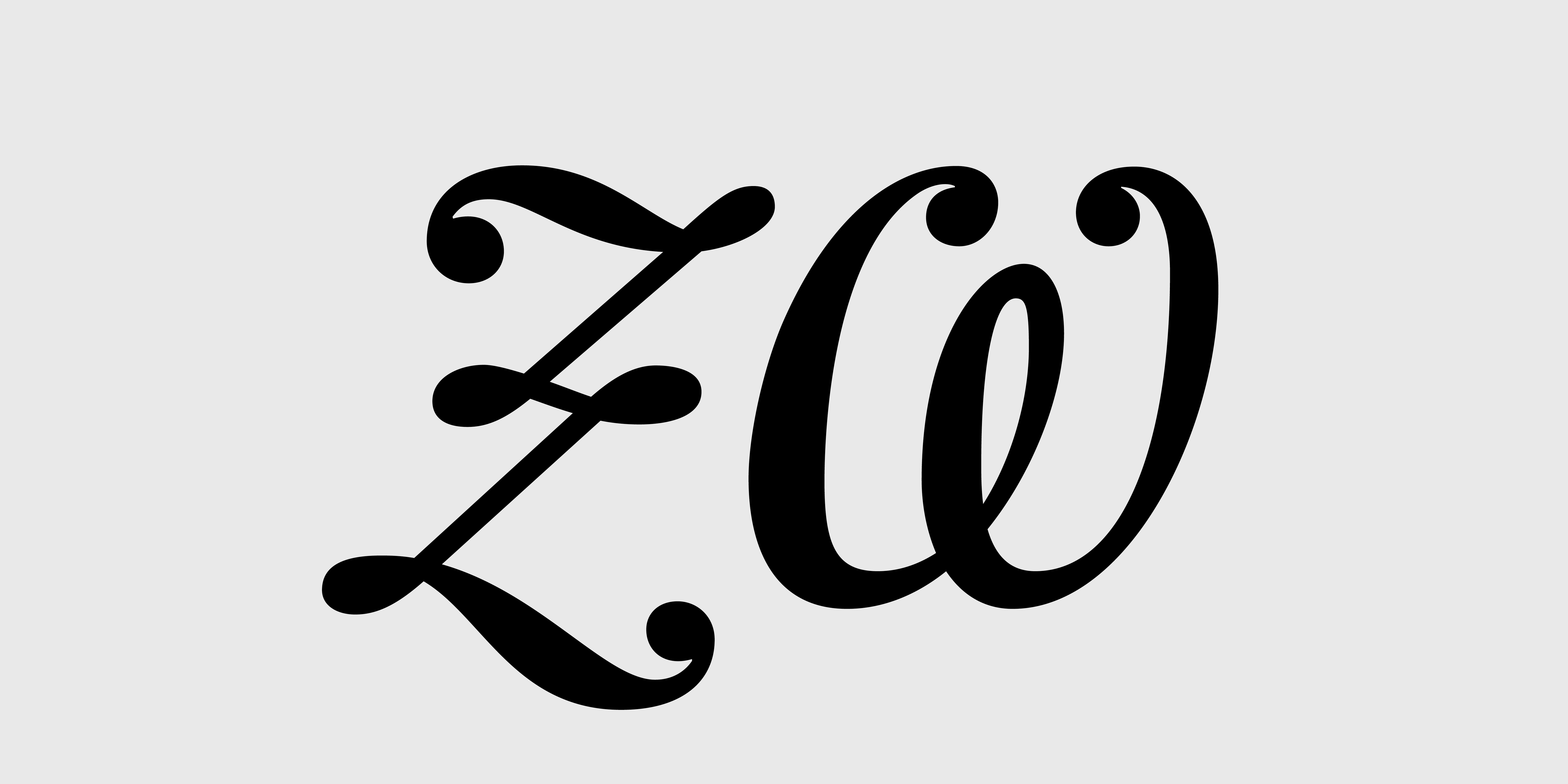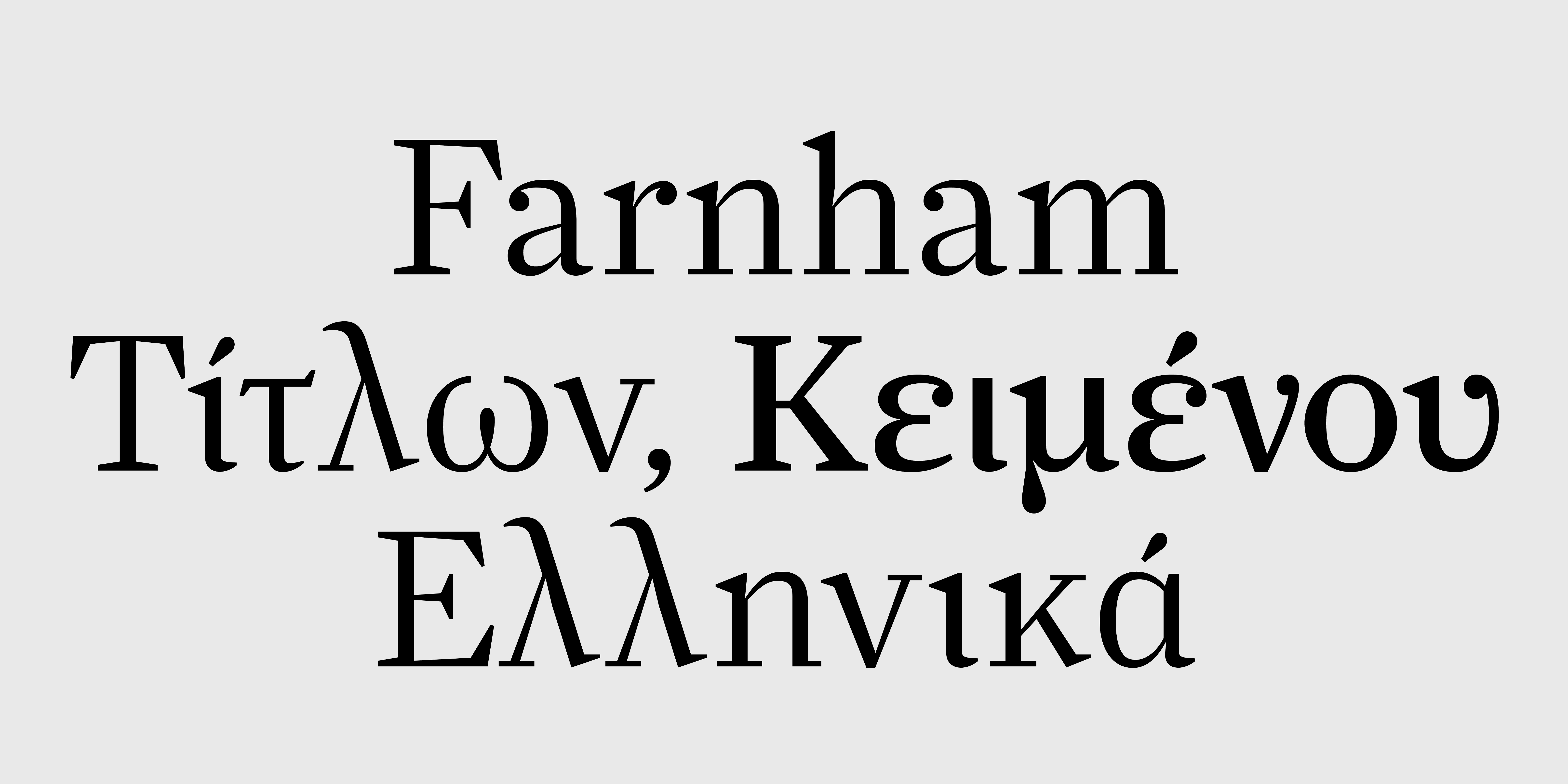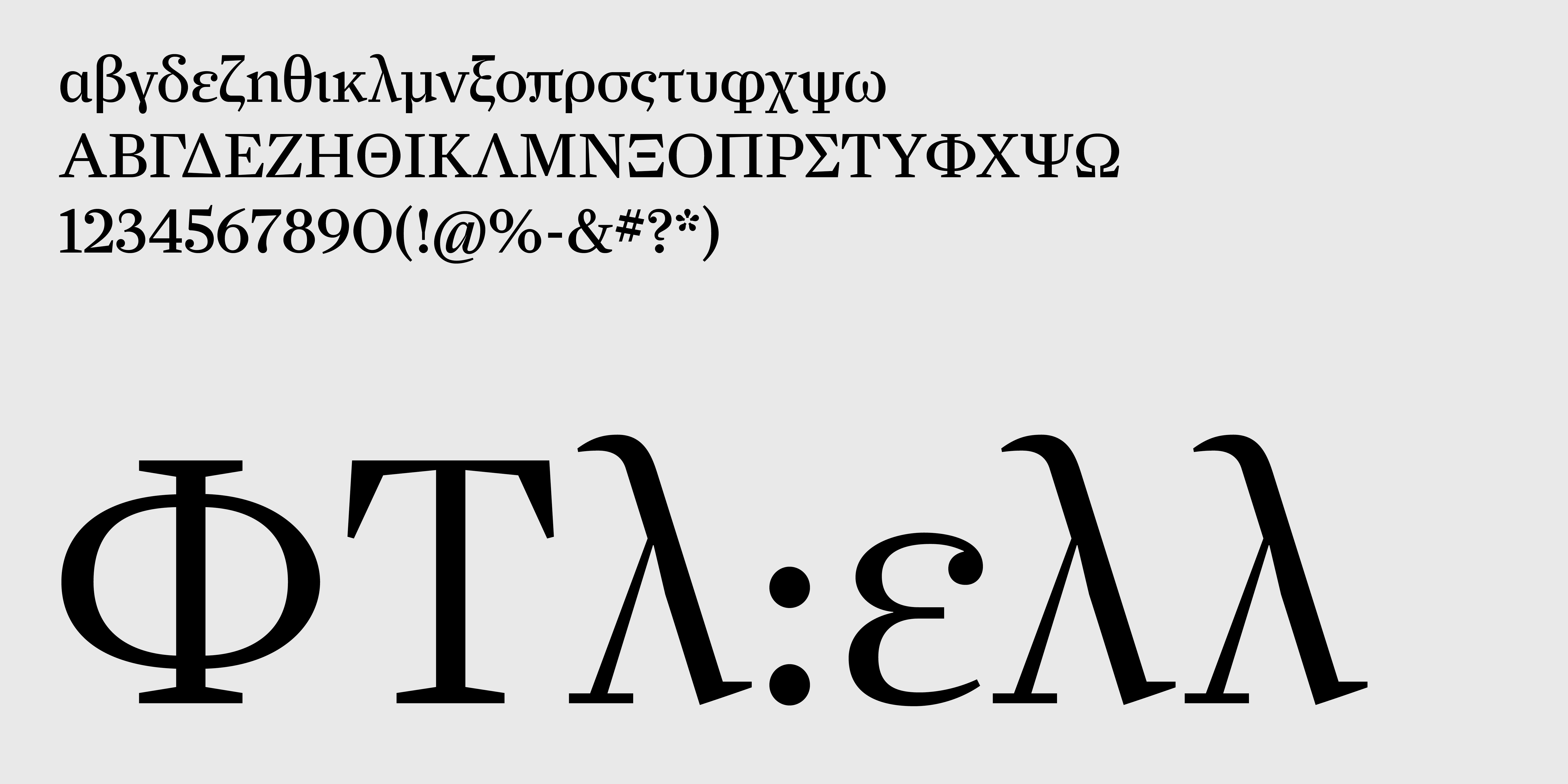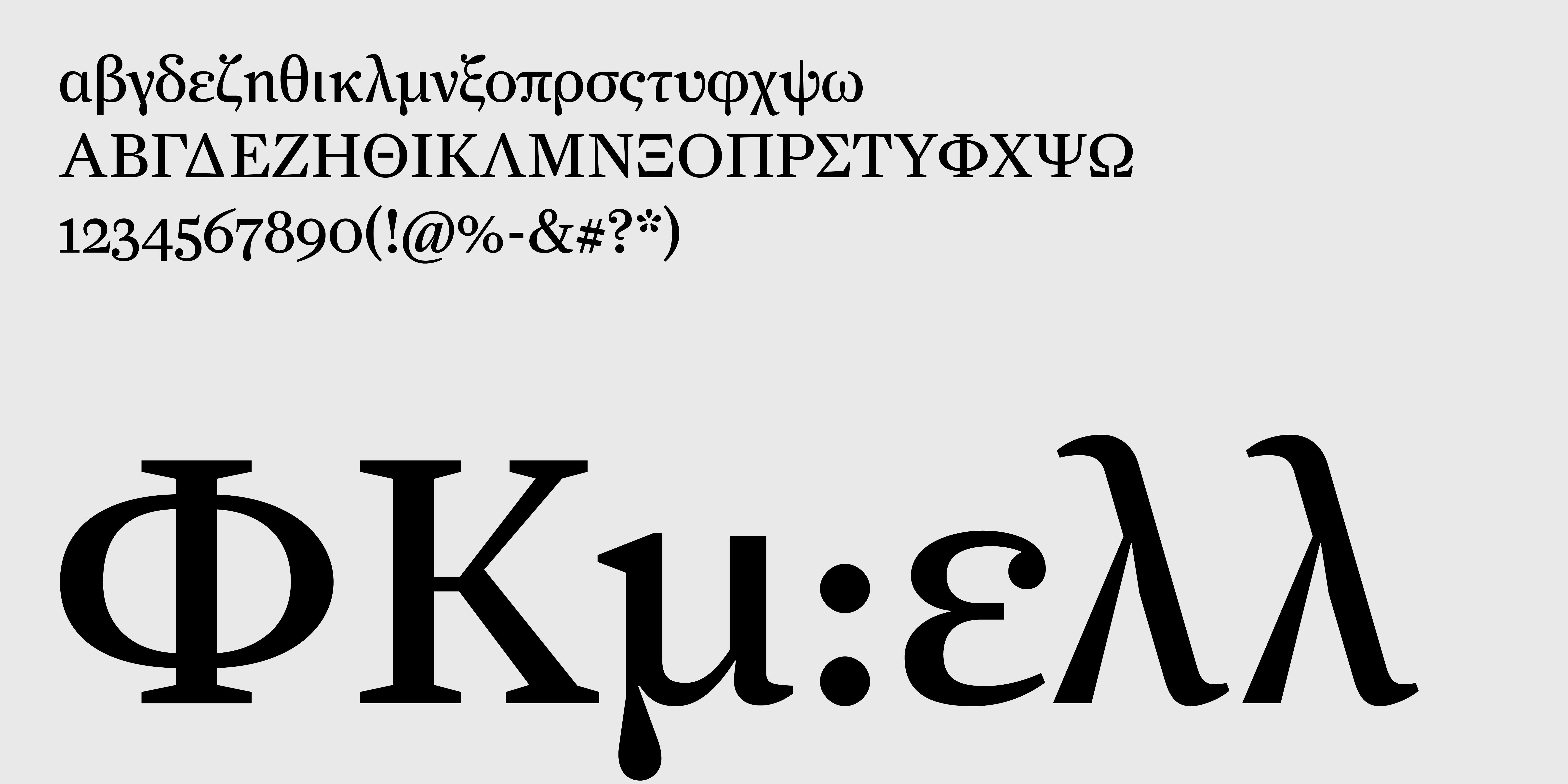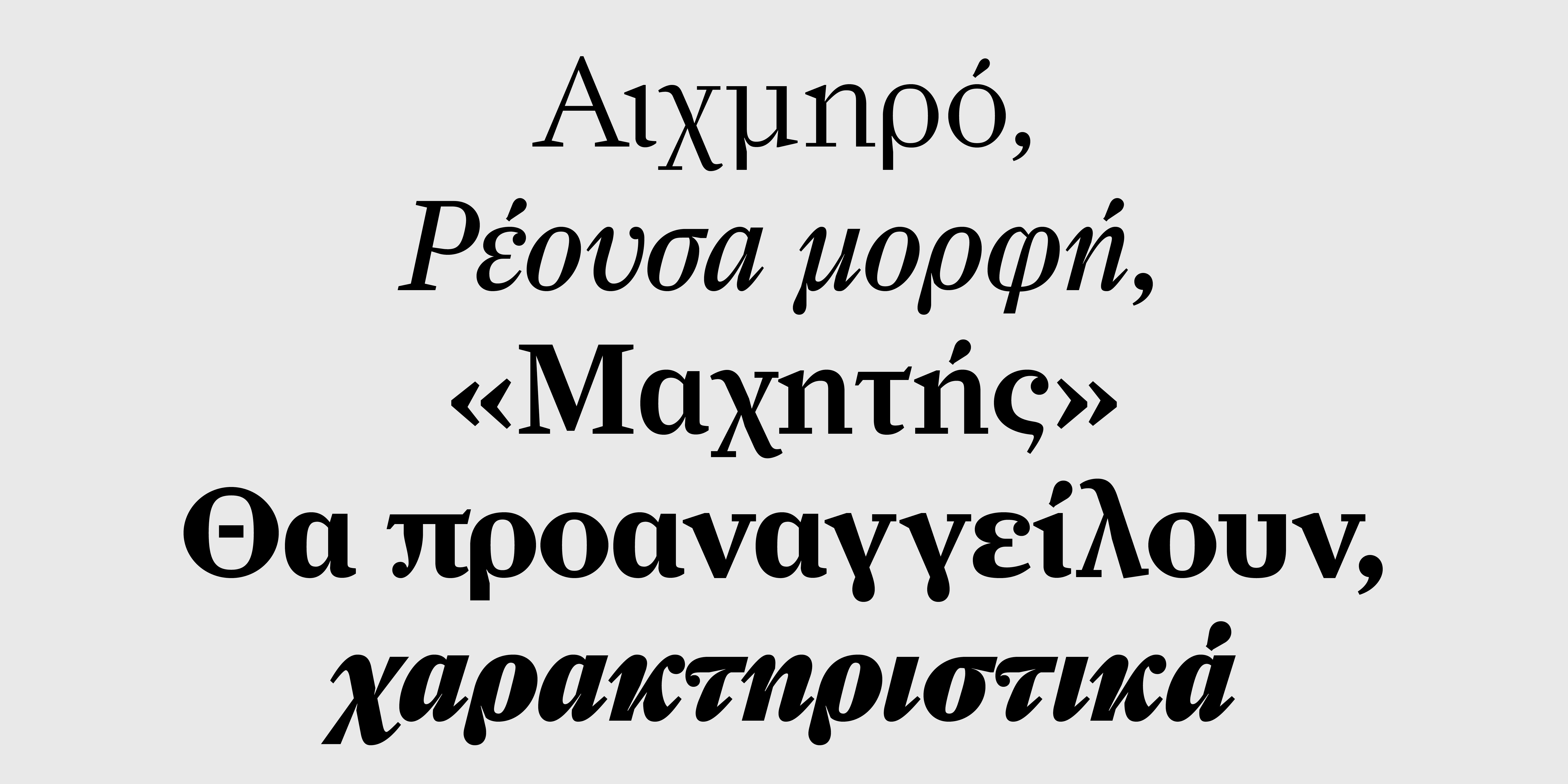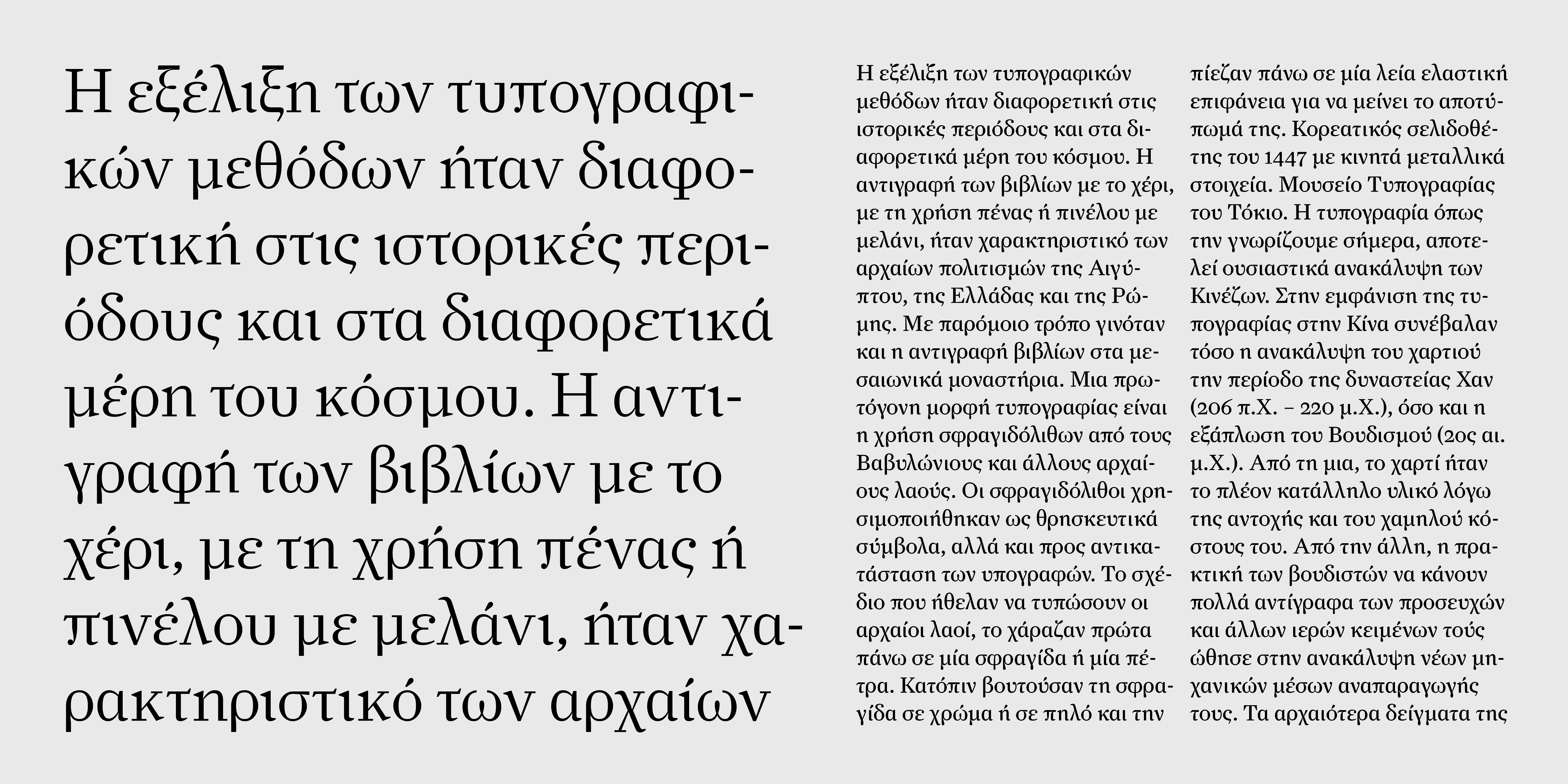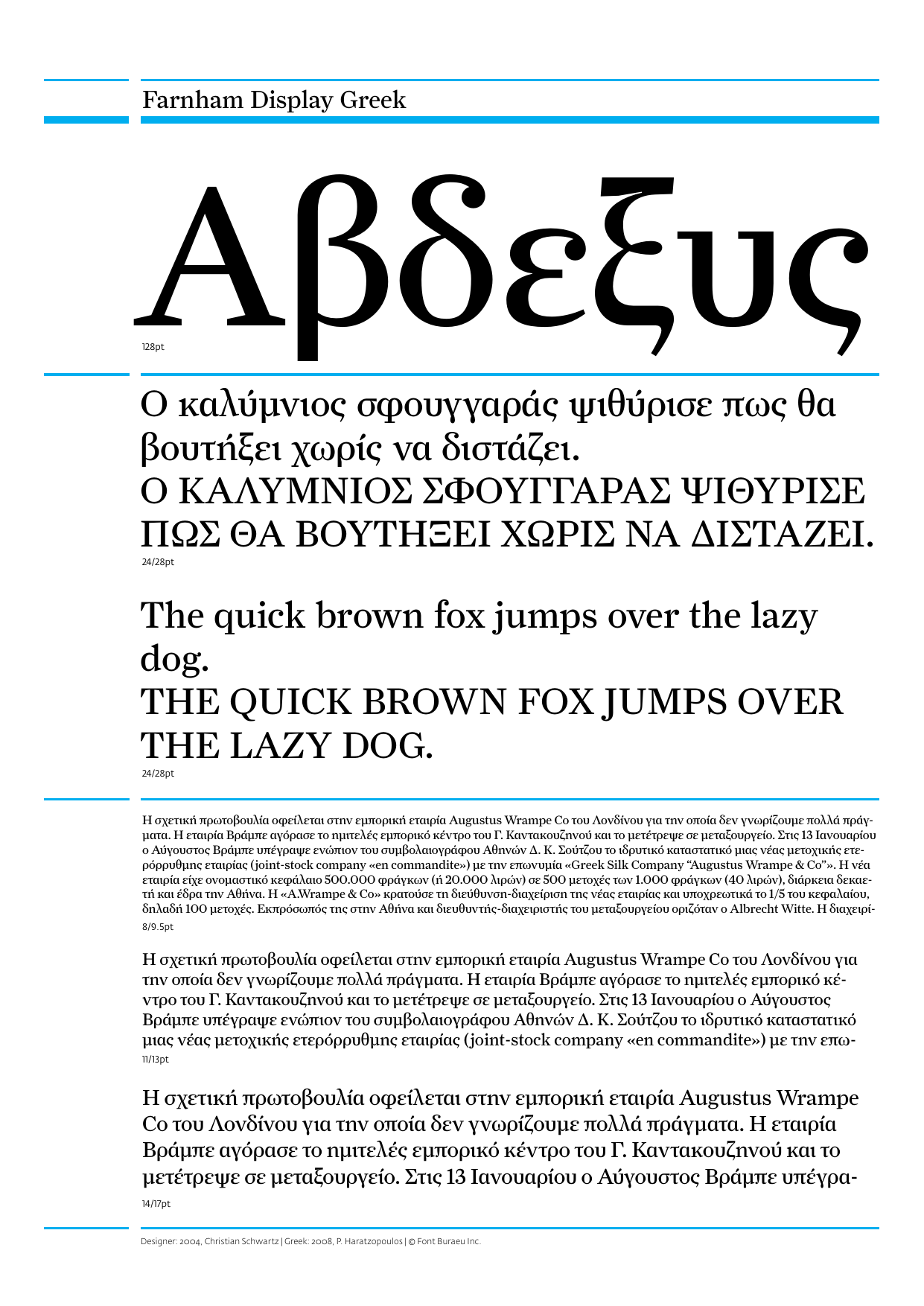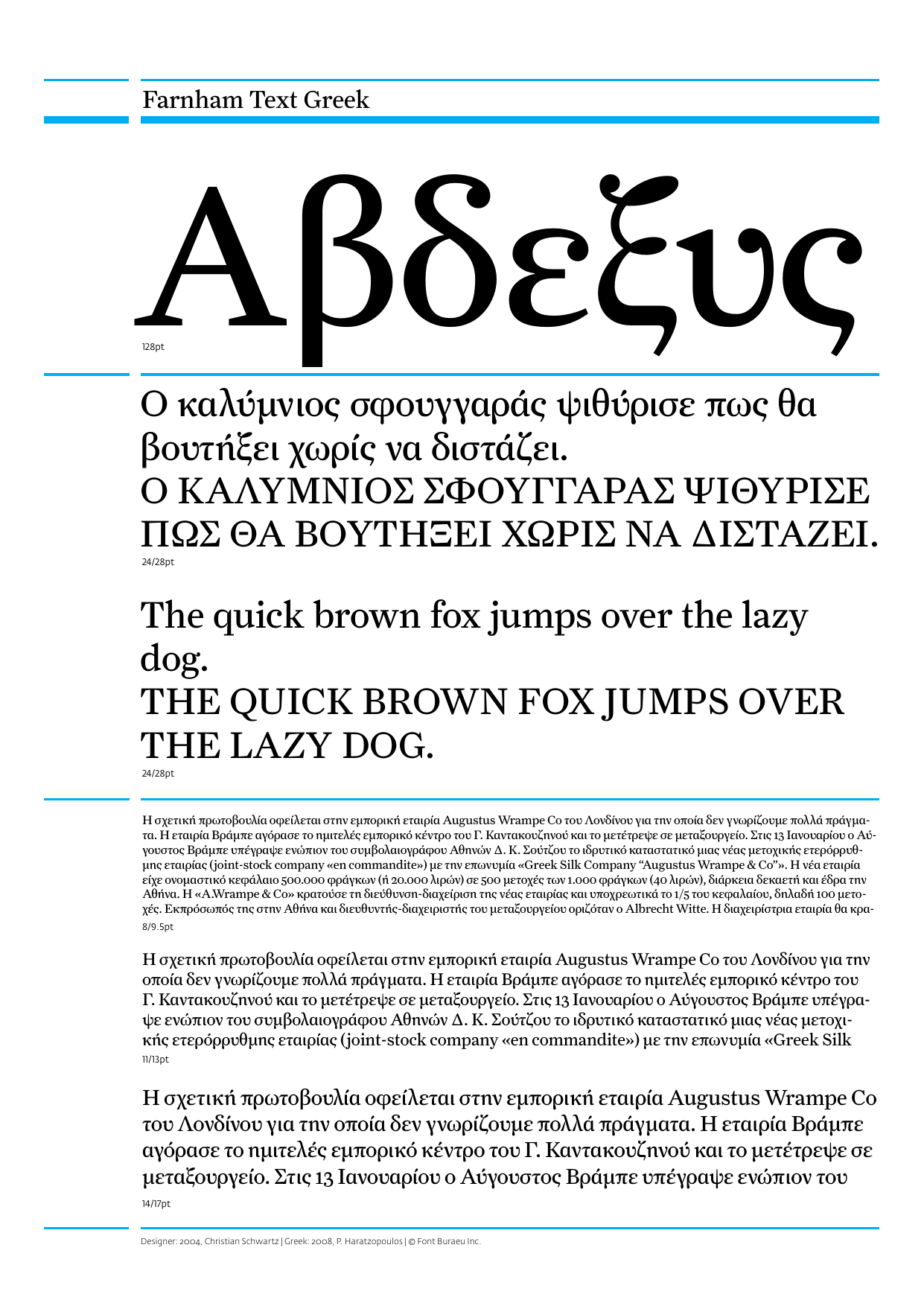
Farnham Ελληνικά Collection
Farnham Display Ελληνικά
Farnham Text Ελληνικά
Τρεις χαράκτες γραμμάτων του δεκάτου ογδόου αιώνα άνοιξαν το δρόμο για τη μετάβαση από την παλαιά παράδοση στο μοντέρνο στυλ του υψηλού contrast και την κάθετη έμφαση, χαρακτηριστικό γνώρισμα του δεκάτου ενάτου αιώνα. Το έργο του John Baskerville στο Μπέρμινχαμ και του Pierre Simon Fournier στο Παρίσι είναι ευρέως γνωστα. Τα γράμματα του Johann Michael Fleischman είναι λιγότερο γνώριμα. Σχεδιαστής Christian Schwartz, Ελληνική έκδοση Παναγιώτης Χαρατζόπουλος